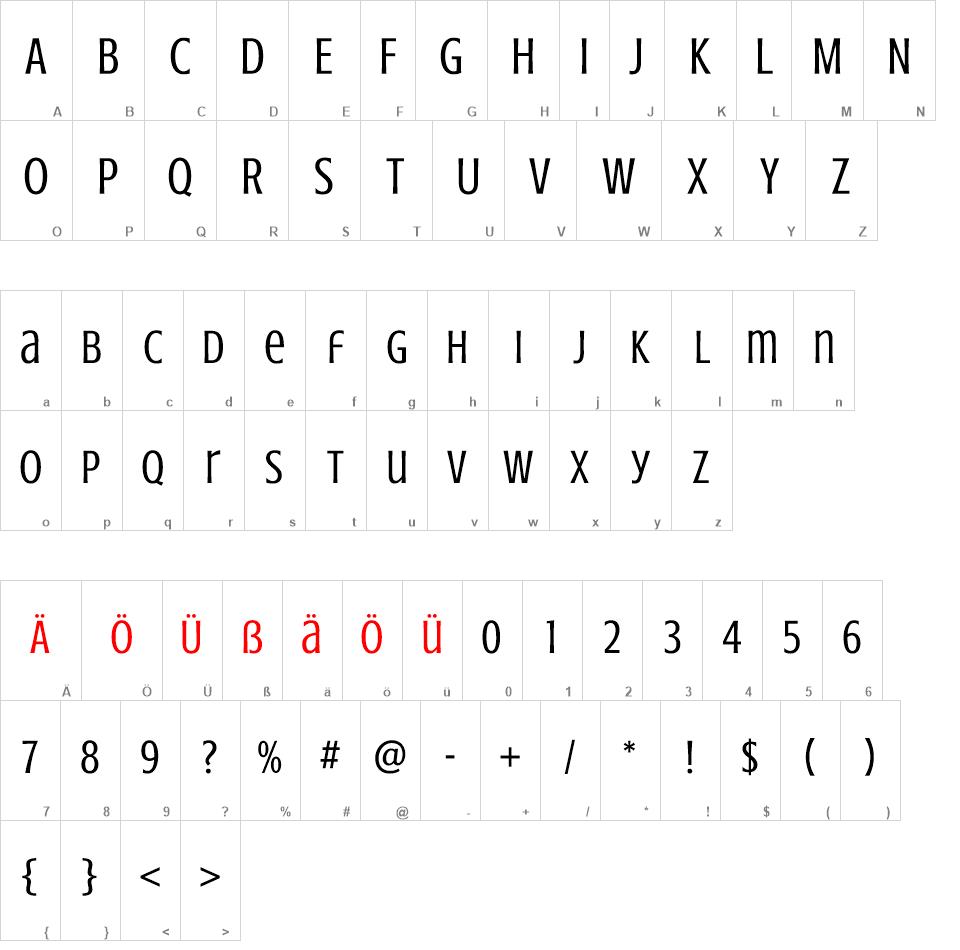
Crushed
Crushed font
Crushed wurde 2010 als Titel- und Bildschirmschrift entworfen. Crushed ist ein Unicase-Design mit einer dichten Körperbreite und sich verjüngenden vertikalen Strichen. Obwohl die Crushed-Schriftart für die Anzeige gedacht ist, sieht sie wirklich gut aus und kann gut in der Textnutzung verwendet werden. Die sanfte Verjüngung der Körper fügt eine gewisse Klasse hinzu und die grundlegenden Buchstabenformen sind modern und frisch.